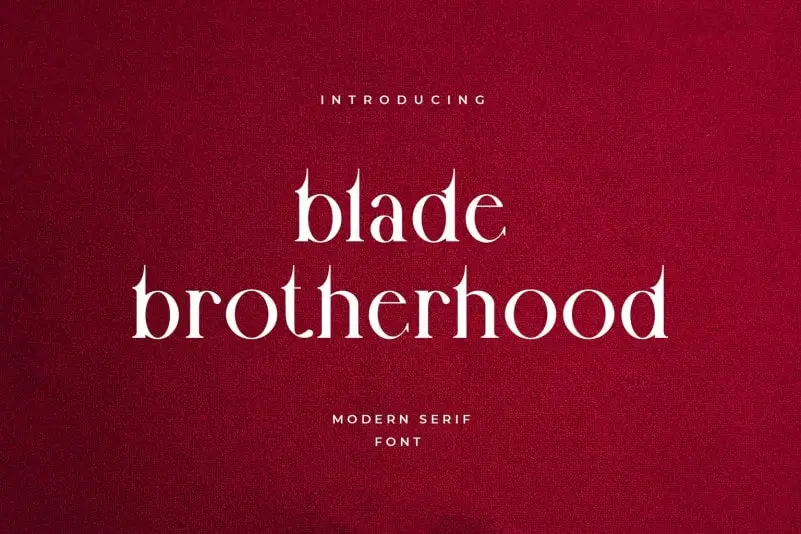
A Blade Brotherhood Serif Font é uma escolha elegante para marcas e projetos que exigem textos bem formados e sofisticados. Este tipo de fontes vem com letras acentuadas, um design moderno clássico e um ar minimalista fashion. Suas letras são tipicamente serifas, mas apresentam uma leve singularidade. Ela se assemelha à um punho afiado no topo da letra, o que lhe confere uma aparência única. Esta fonte premium é perfeita para diversos tipos de projetos, como hoteis, salões, restaurantes, cafés, headlines, cartazes, comunidades, marca e embalagens. Ela também se destaca em apresentações e textos curtos. É uma ótima escolha para aqueles que desejam dar um toque de sofisticação e elegância a seus projetos visuais.